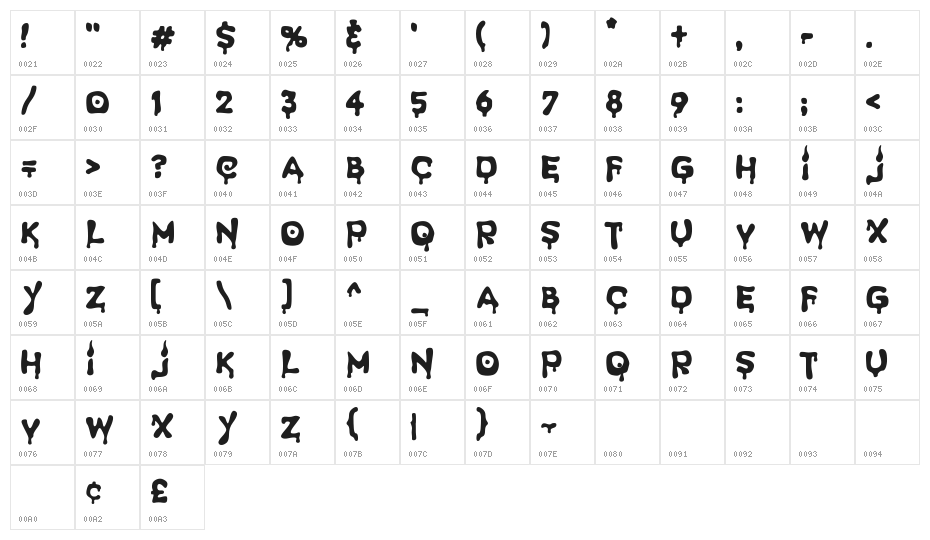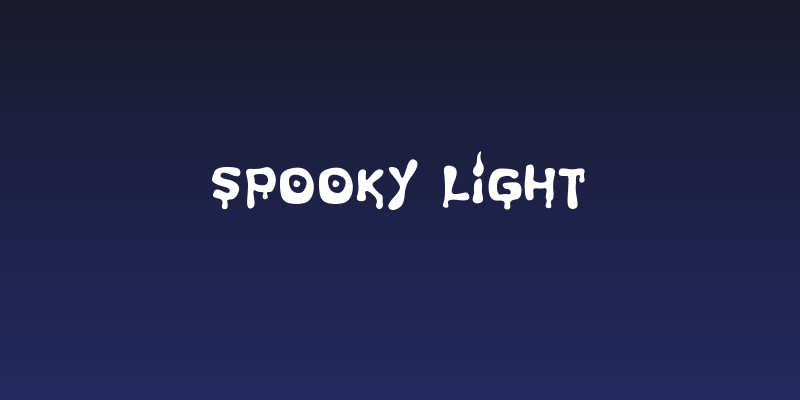
Spooky Light Font
| Progetti proposti | Ideal for Halloween invitations, themed posters, children's book covers, or any project needing a whimsical and eerie touch. |